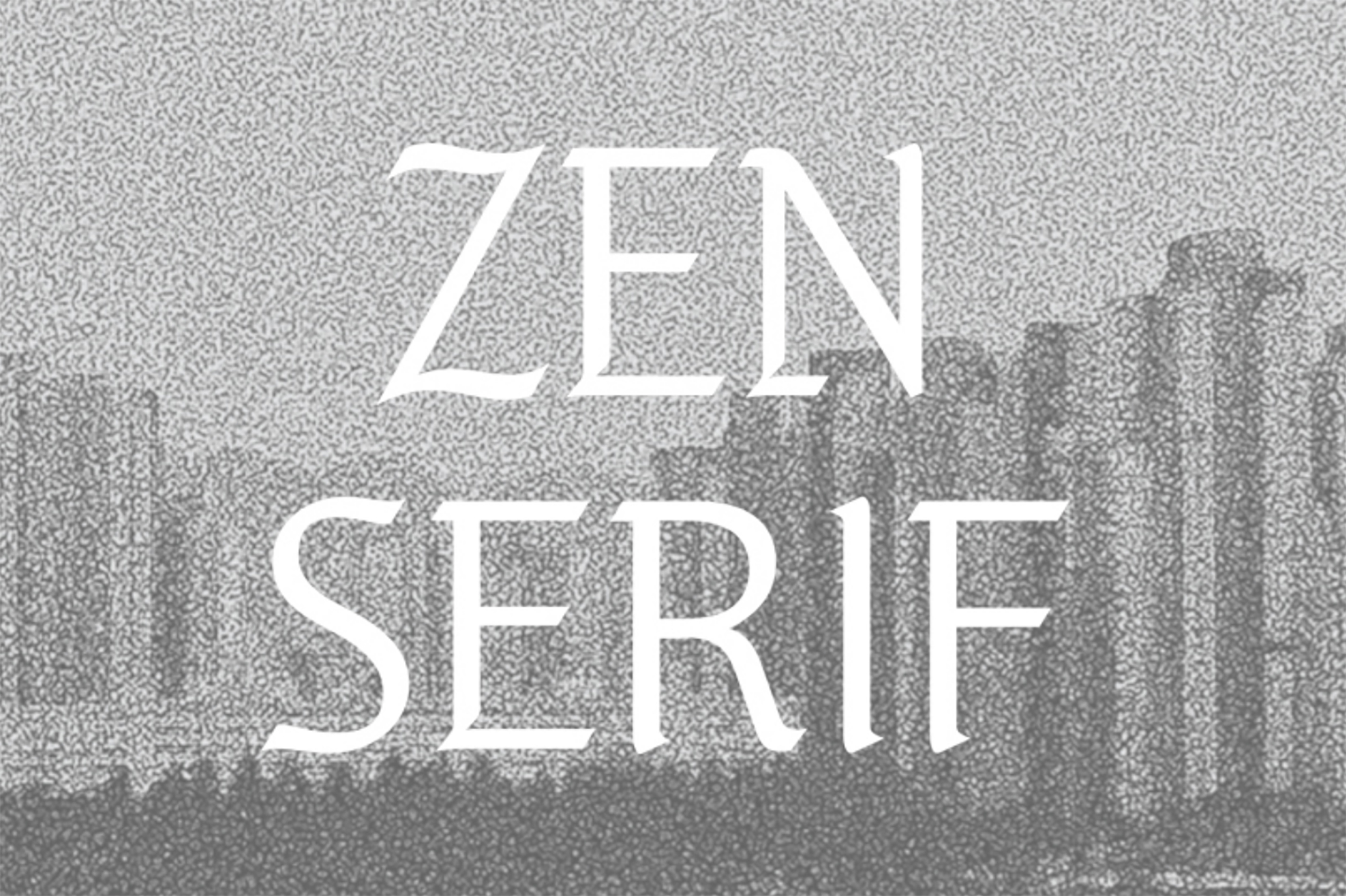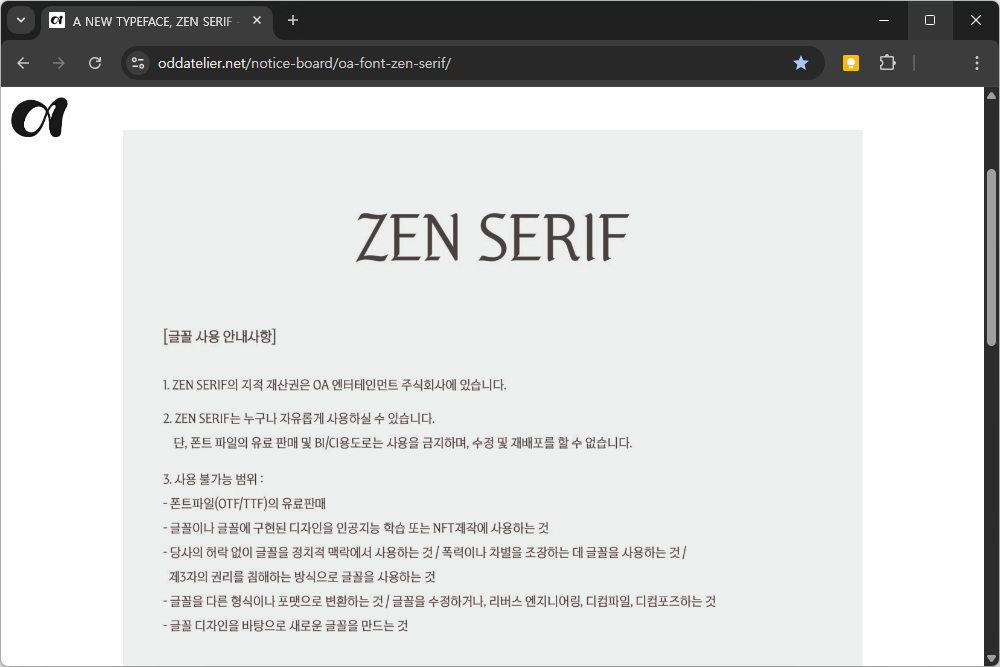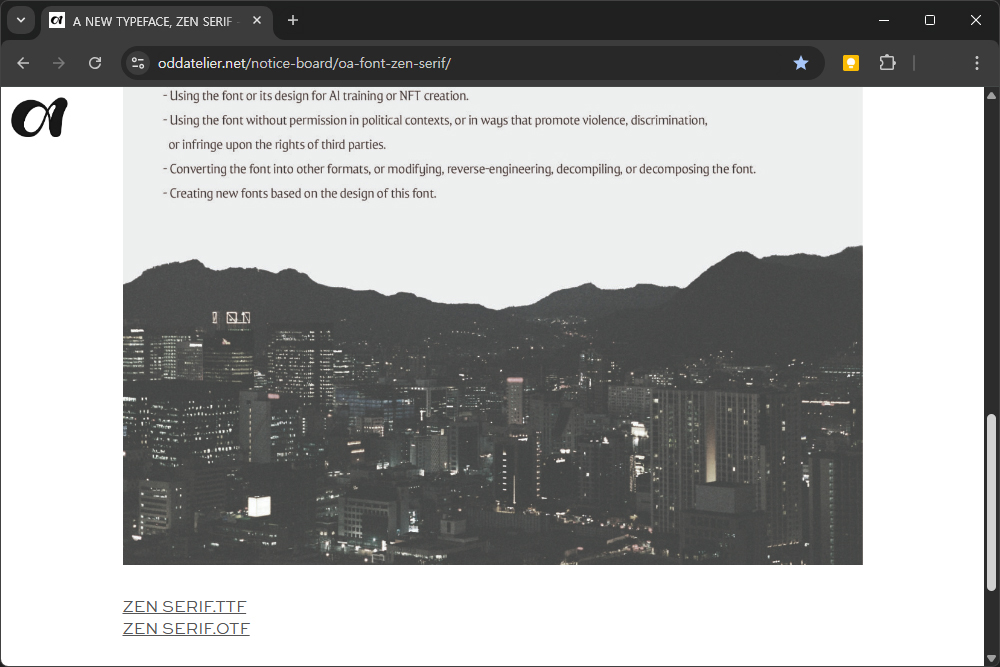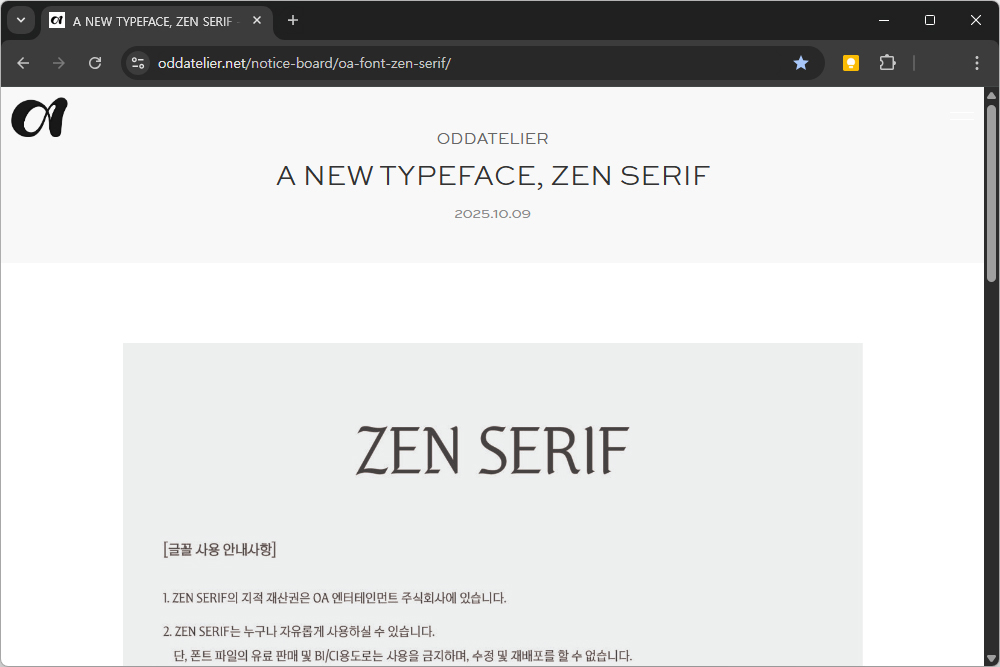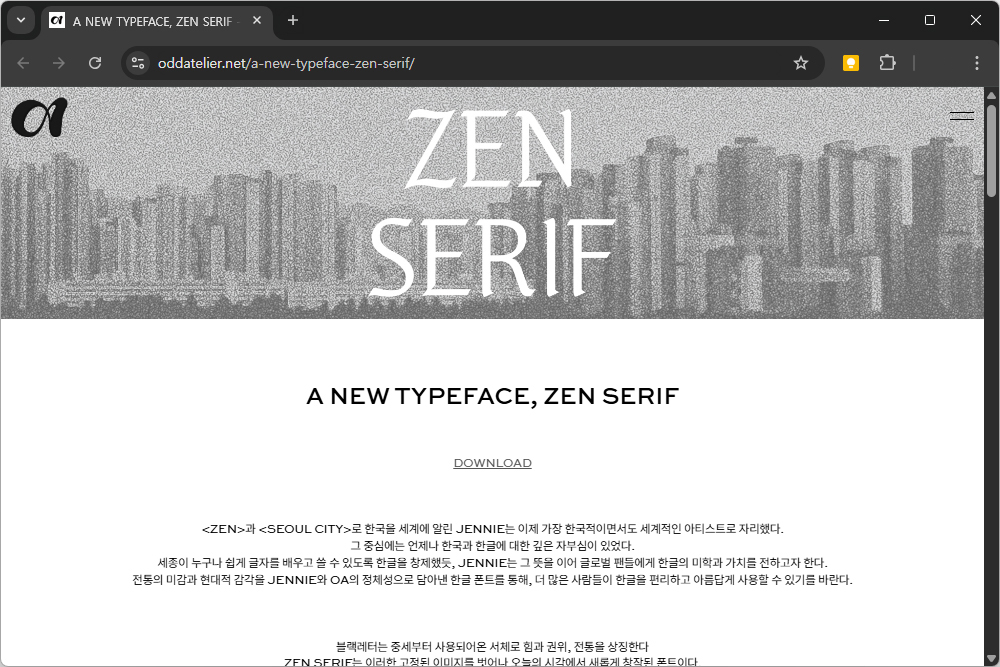
한글날 기념 블랙핑크 제니 폰트 ZEN SERIF 다운로드와 설치 방법
2025년 한글날을 기념해서 다양한 회사들이 무료 글꼴을 배포했는데요. 가장 저의 눈길을 끈 폰트는 블랙핑크 멤버인 제니가 발표한 ZEN SERIF라는 서체였습니다. 케이팝 K-POP 아티스트가 발표한 아마도 첫 번째 폰트라고 상당한 의미가 있다고 판단되는데요. 이번 포스팅에서는 다운로드와 설치 방법을 자세하게 확인해 보도록 하겠습니다.
우선 홈페이지에 접속하면 폰트에 대한 정보를 확인할 수 있는데요. 전통의 미감과 현대적인 감각을 JENNIE와 OA의 정체성으로 담아내서 제작했다고 합니다. 참고로 여기에서 OA는 ODD ATELIER(오드 아틀리에)로 제니가 설립한 연예 기획사입니다. 실제로 폰트를 어떤 회사에서 제작했는지는 아직 알려지지 않았습니다.
“의미 있는 시도”
이번 제니 ZEN SERIF 폰트는 상당히 의미 있는 시도라고 생각이 되었습니다. 그리고 결과물도 상당히 훌륭한 편이어서 다양한 용도로 활용할 수 있을 것으로 보입니다. 그리고 내년에도 이러한 의미 있는 시도들이 계속 이어지길 바랍니다.